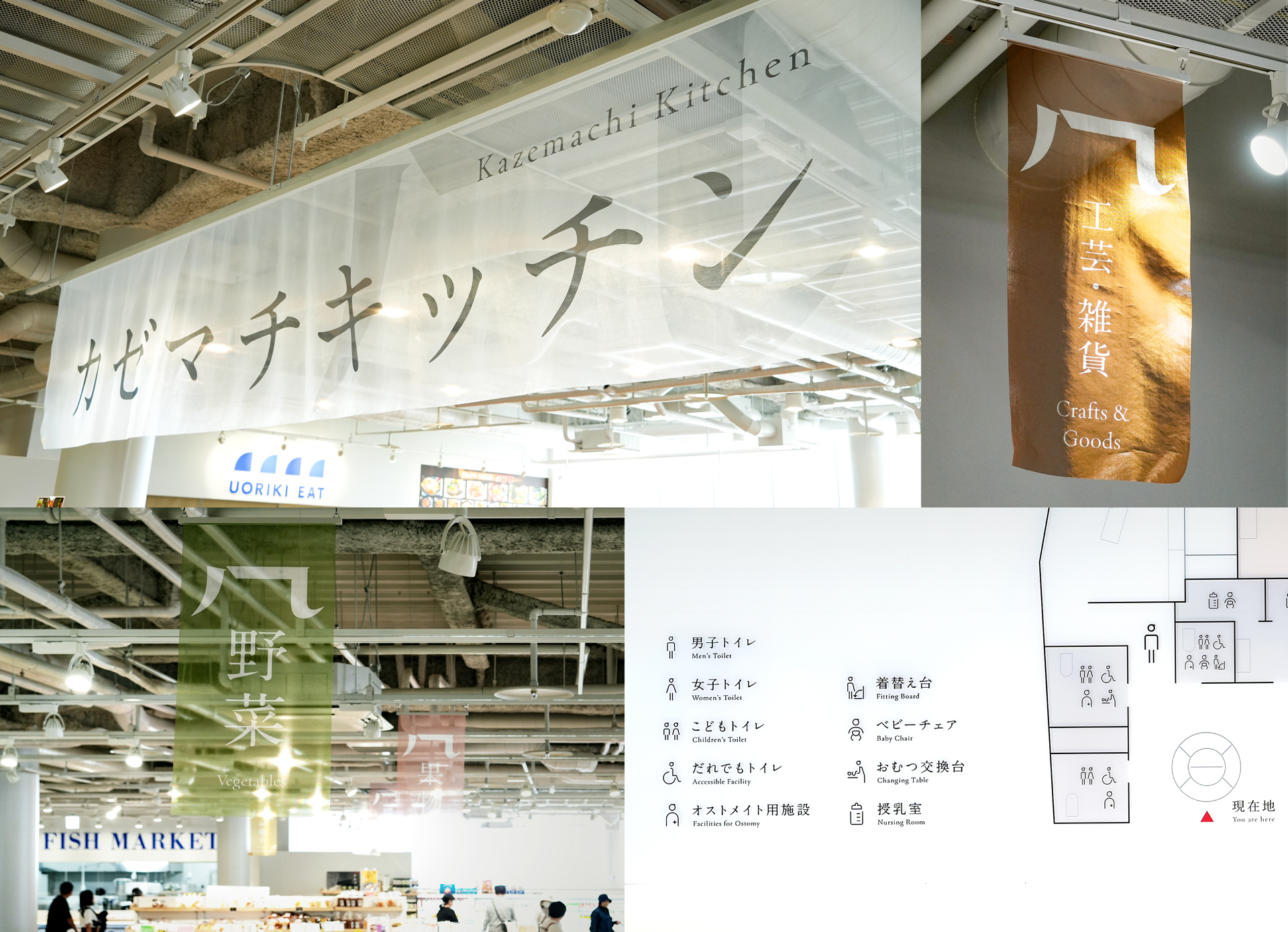
モリサワ 佐賀県上峰町の中心市街地活性化事業としてオリジナルフォント「カゼマチ明朝」を開発!町のあらたなランドマーク「道の駅かみみね」に採用
株式会社モリサワ(以下モリサワ)は、佐賀県上峰町の中心市街地活性化事業として、まちづくりの想いを視覚的に表現したオリジナルフォント「カゼマチ明朝」を開発しました。
- カゼマチ明朝が使用された「道の駅かみみね」の案内サイン
上峰町中心市街地活性化事業は、佐賀県上峰町および民間事業者による合同会社つばきまちづくりプロジェクトが取り組む事業です。
カゼマチ明朝は、つばきまちづくりプロジェクトとともにデザインの検討を行い、やわらかな印象と自然な温かみを感じさせる「A1明朝」をベースに開発を進めました。線が交差する部分には“墨だまり”の表情が再現され、やや平体ぎみのプロポーションとなっていることが特徴です。独特の味わいを感じさせるカゼマチ明朝は、まちづくりのコンセプトである『自由が吹く。』という言葉とも呼応するデザインとなっています。
オリジナルフォントの導入により、景観としての統一感や地域ブランディングの効果が高まることはもちろん、住民の皆様の地域への愛着やアイデンティティがより一層醸成されることを目指しています。
今後は施設内外の案内サインや看板、キャプションなど、さまざまな場面でこのフォントが活用される予定です。